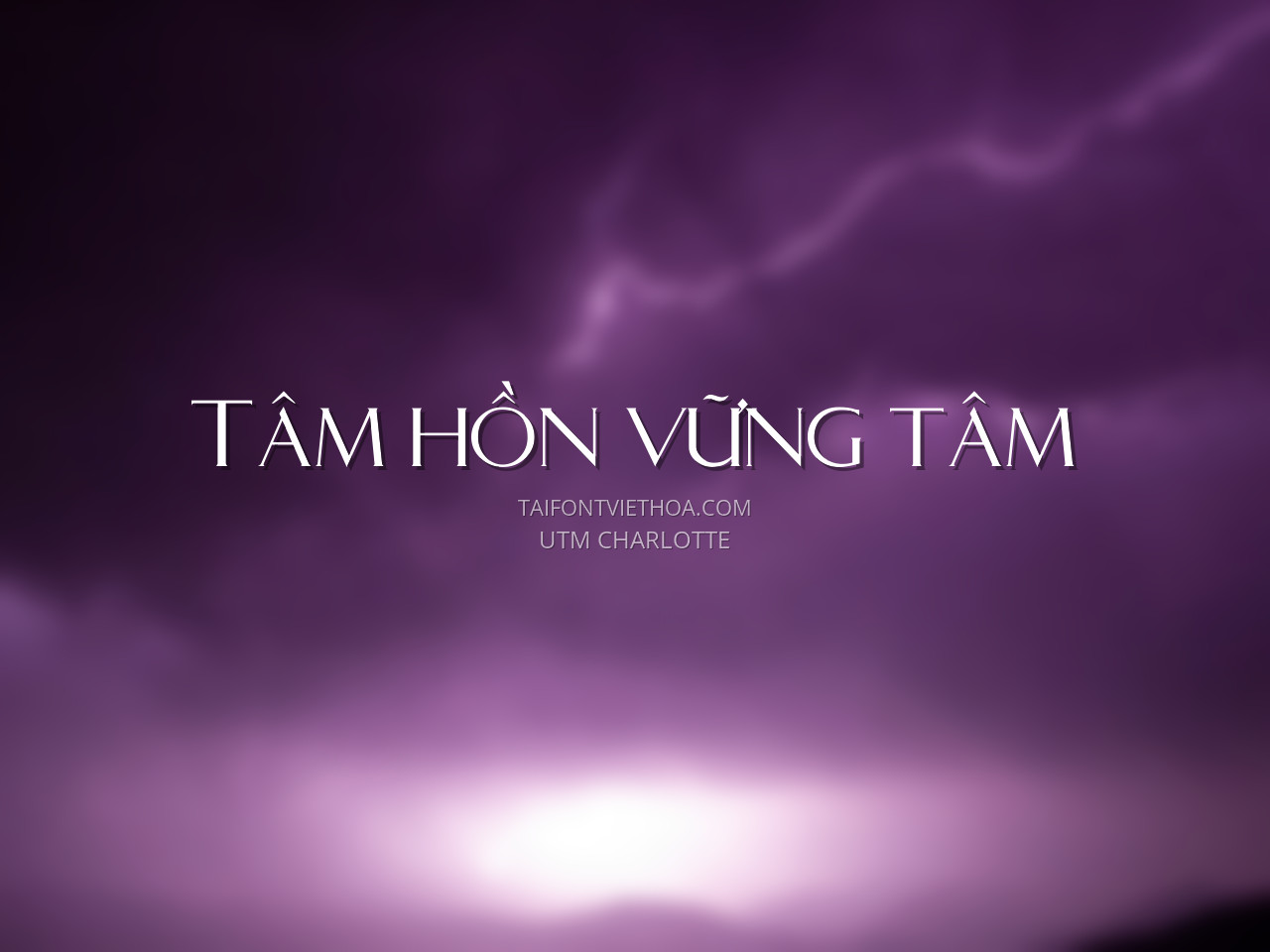
Giới thiệu về font UTM Charlotte
UTM Charlotte là phiên bản Việt hóa của font Charlotte – một kiểu chữ serif thanh lịch và hiện đại, được thiết kế nhằm kết hợp giữa nét cổ điển và phong cách tối giản đương đại. Font gốc nổi bật với các nét chữ có chân (serif) sắc nét, tỉ lệ cân đối và độ tương phản hài hòa, tạo nên sự tinh tế và dễ đọc trong mọi kích thước. Phiên bản Việt hóa đã được phát triển để hỗ trợ đầy đủ tiếng Việt cùng hơn 200 ngôn ngữ khác, mở rộng khả năng ứng dụng trong các dự án thiết kế chuyên nghiệp.
Đặc điểm thiết kế và ứng dụng của UTM Charlotte
UTM Charlotte sở hữu cấu trúc serif với các nét chân chữ sắc nét, độ tương phản vừa phải và thiết kế cân đối, tạo nên sự hài hòa và dễ đọc. Font có nhiều biến thể trọng lượng, giúp các nhà thiết kế linh hoạt sử dụng cho tiêu đề nổi bật và nội dung chi tiết. Thiết kế font mang lại cảm giác chuyên nghiệp và sang trọng.
Font thích hợp sử dụng trong thiết kế sách, tạp chí, thiệp cưới, danh thiếp, bao bì sản phẩm cao cấp và các ấn phẩm thương hiệu sang trọng. Các ngành nghề phù hợp gồm: xuất bản, thời trang, tổ chức sự kiện, nghệ thuật, giáo dục và thiết kế nội thất.